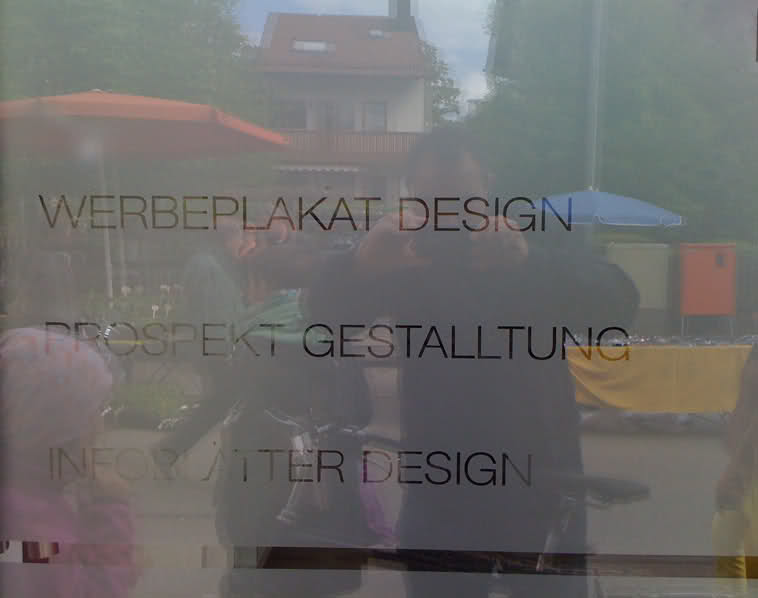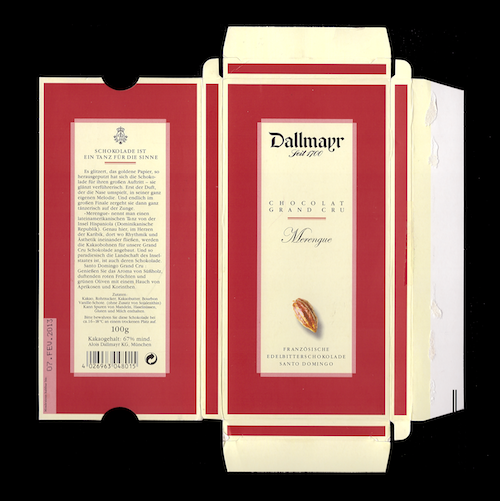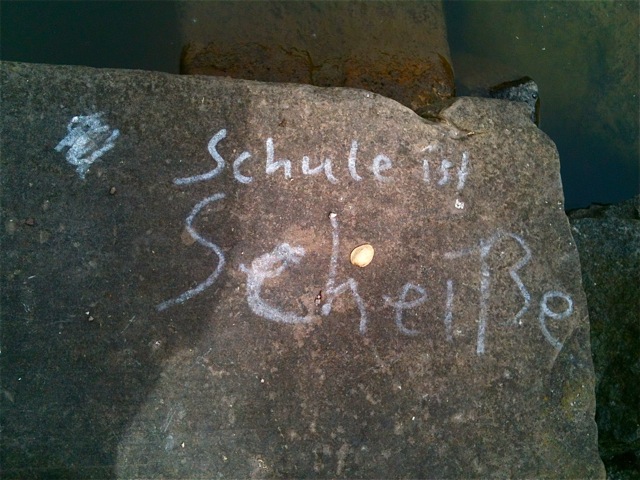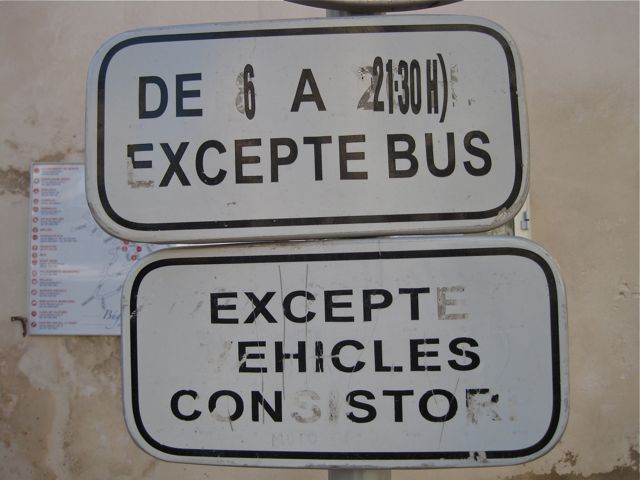
Das soll aussehen wie Nessie (Loch Ness), weil der Erfolg von Steuerberatung genauso ein Mythos ist. :!:
Das wird’s sein. Diese Antwort kann ich als die einzig richtige akzeptieren :-)
Hier mal eine schöne Schokoladenverpackung.
Ich radl da jeden Tag dran vorbei … heute hab ich mal gebremst ;-)
Das wird eine Heidenarbeit, bis alle Rechtschreibfehler korrigiert und alle fehlenden Koppelstriche ergänzt sind … ;-) Aber wenigstens haben sie Gestalltung stringent falsch geschrieben, das steht nämlich in vier Wortkombinationen viermal falsch.
Tja, wenn man schon was falsch macht, sollte man das wenigstens richtig machen. Aber wer wird sich auch bei solchen Kleinigkeiten wie Orthographie aufhalten, wenn er damit beschäftigt ist, mit Hilfe der Helvetica (extended! light!) ein unverwechselbares und einprägsames Design mit höchstem Identifikationswert zu schaffen.
… aber immerhin erlernt man ja dort offensichtlich trotzdem des schreibens wortige mächtigkeit. oder mokierte sich hier gar eine lehrperson? zu tiefe löhne an deutschlands schulen? (gotha, schlosspark, mai 2012)
Wird in der Schweiz besser bezahlt? Nicht, dass die schweizer Schulen noch von deutschen Lehrern überschwemmt werden ...;-):lol:
in einem blog martin z. schröders über die schöne «fundamental» habe ich eben diesen verweis gefunden, den ich für zeigenswert halte.
Mühlentag: Eins, zwei
Sehr schön! Ich nehme an, dass das zweimal abgebildete Halle a/S. für »Halle anner Saale« steht? (Ansonsten hätte ich ja eher »Halle/S.« oder »Halle a/d/S.« vermutet.) :roll:
Ich vermute mal, daß durch mannhafte Flüsse wie Rhein und Neckar Abkürzungen wie a/R. oder a/N. so verbreitet waren, daß man dann auch bei der Saale nach dem Schema a/Fluß verfuhr. Aber das ist nur geraten. Heute würde man solche grammatische Diskriminierung weiblicher Flüsse natürlich strikt vermeiden.
Da man könnte a/R. ja auch als an dem Rein verstehen, insofern ist auch an der Saale möglich. Alternativ kann man, wenn a/R. zu am Rein wird, a/S. auch zu anner Saale machen :hammer:
Und schreibt man ich nicht Frankfurt a.M. und Frankfurt a.O. statt Frankfurt a.d.O.